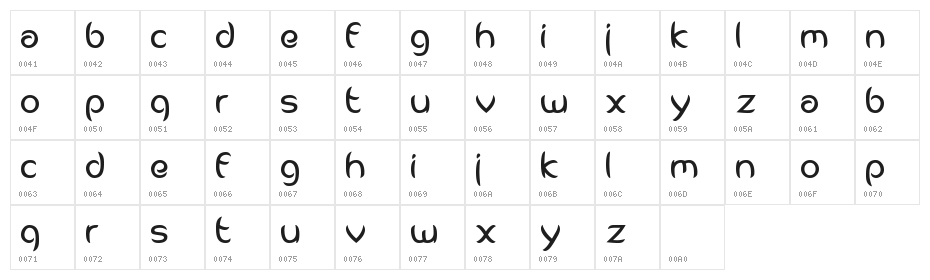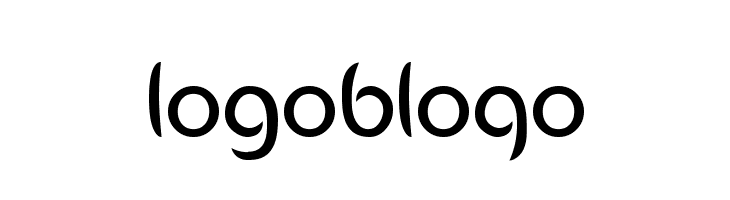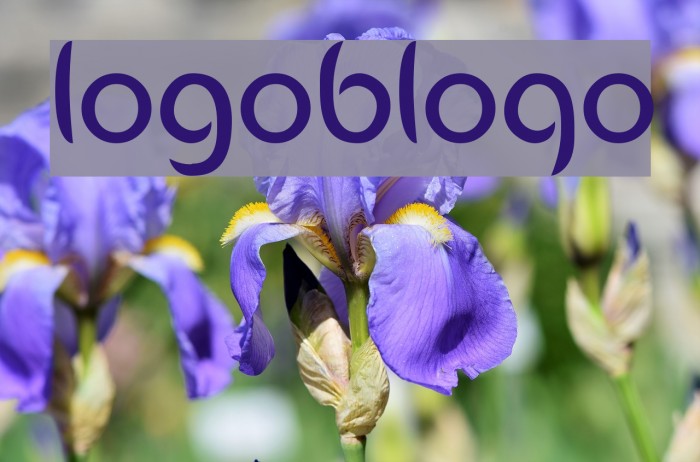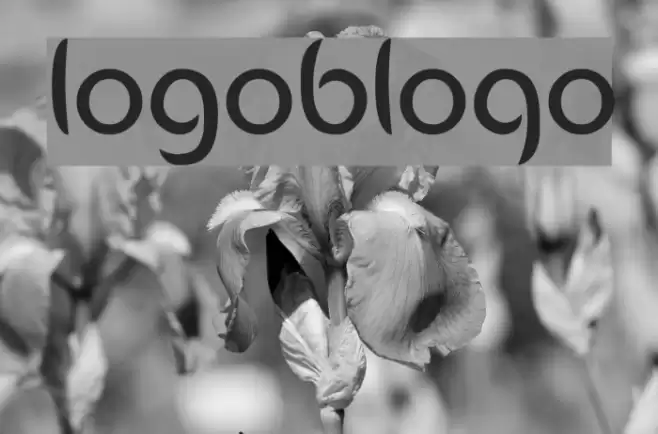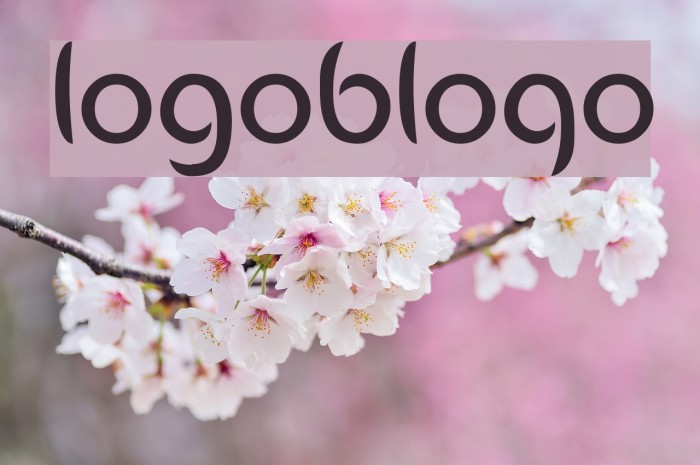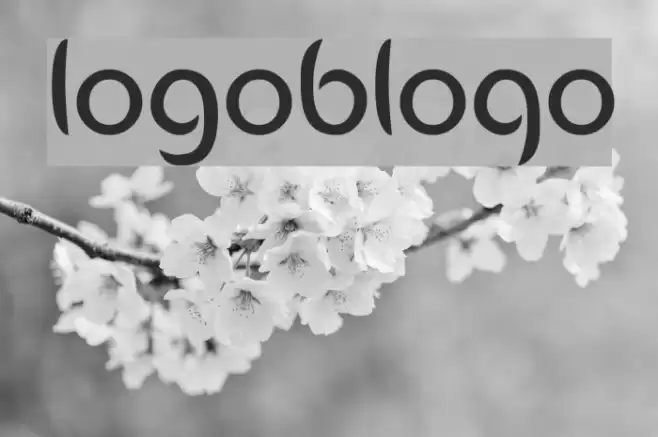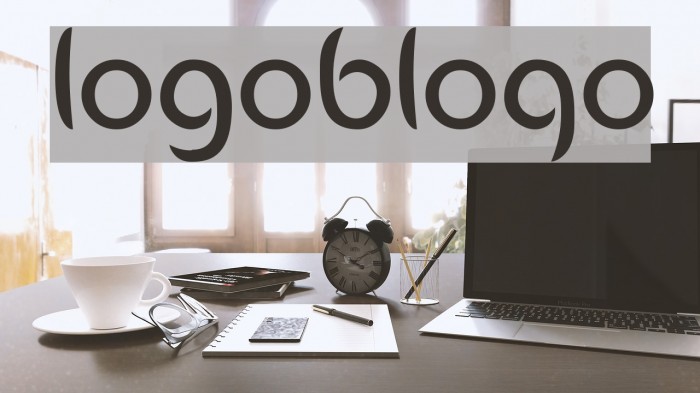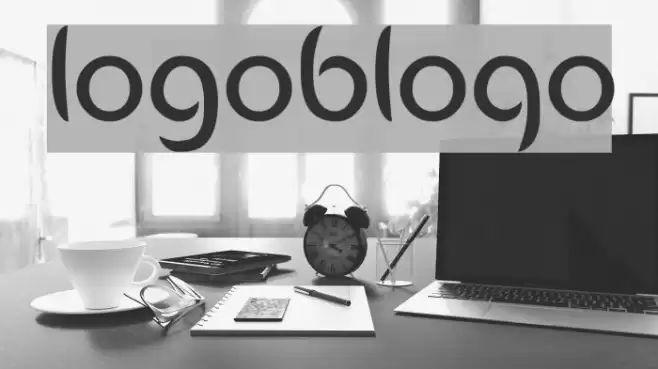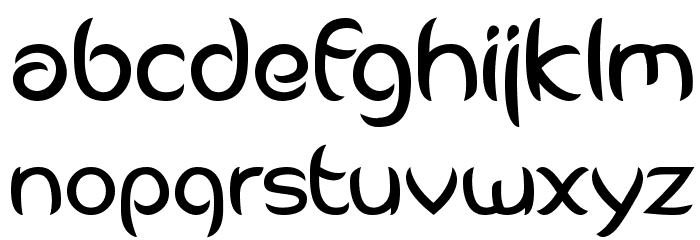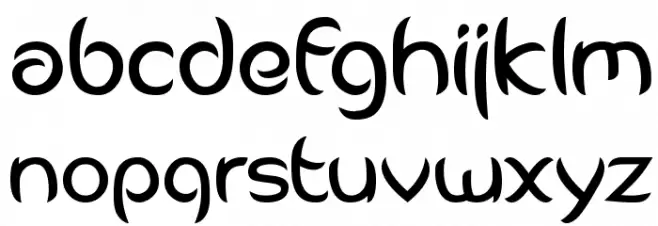
Logobloqo2 Font
| Cas d'utilisation | Logos, Headlines, Branding |
| Projets proposés | Ideal for children's books, playful branding, creative logos, and casual invitations. |